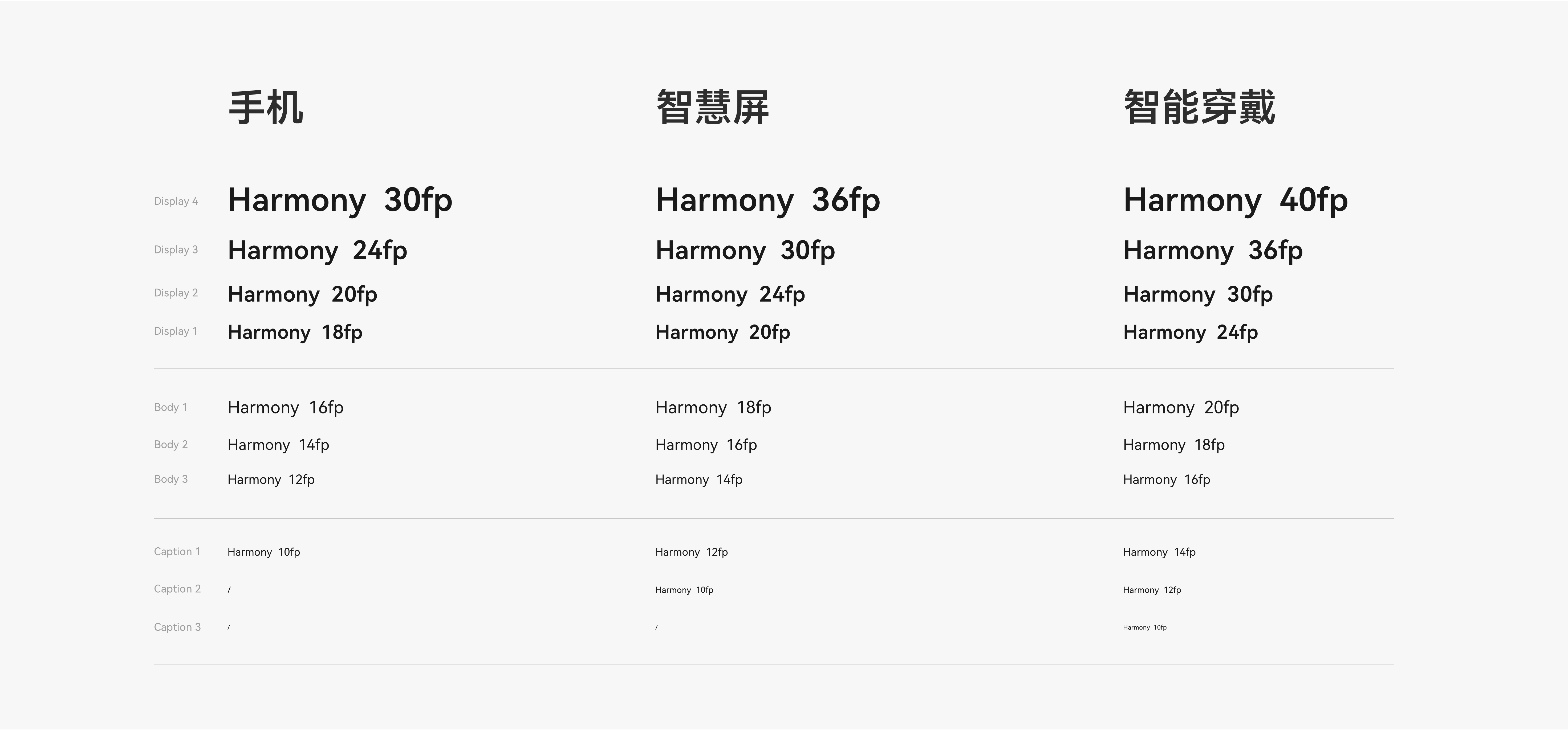
鸿蒙字体
华为鸿蒙字体 (HarmonyOS Sans),华为定制字体,为鸿蒙OS一同上线,于2021年6月发布上线,可以免费商用。设计上聚焦于功能性、普适性,是一款多语言的无级可变字体,该字体支持简体中文、繁体中文、拉丁、西里尔、希腊、阿拉伯等5大书写系统,105种语言全球化覆盖。
通过研究用户在不同场景下对多终端设备的阅读反馈,综合考量不同设备的尺寸、使用场景等因素,同时也考虑用户使用设备时因视距、视角的差异带来的字体大小和字重的不同诉求,华为为 HarmonyOS 设计了全新系统默认的字体——HarmonyOS Sans,该字体拥有以下特性:
易读:中文笔画复杂,HarmonyOS Sans在设计时为应对可变字体笔画连接处易破碎的情况,做出优化统一处理,使得字体最终呈现效果干净而利落。
独特:HarmonyOS Sans字体笔画优化,削弱了黑体的机械感;采用现代感结构处理;笔画造型融入了书写美感。
通用:HarmonyOS Sans字体比Roboto更显大更显宽,与中文匹配度更高,同时对符号设定了多种与文字相匹配的排版属性;在深色模式下使用了更细的字重,让字体的视觉粗细与浅色模式保持一致。